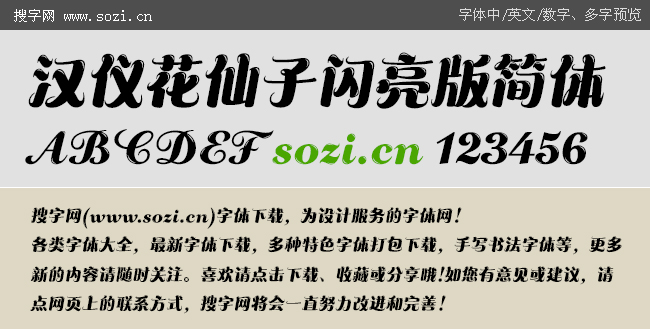
漢儀花仙子閃亮版簡體
搜字網(wǎng)給大家提供一款漢儀花仙子閃亮版簡體中文字體下載,漢儀花仙子閃亮版簡體字體從西文點(diǎn)尖書法中獲取靈感,西文書寫的優(yōu)美曲線與漢字書寫的規(guī)整造型碰撞,生長出了一款極繁主義的中文花體字。字形飽滿而圓潤,以流動(dòng)曲線構(gòu)成的筆畫似植物花卉的曼妙姿態(tài),連筆設(shè)計(jì)與裝飾游絲點(diǎn)綴其間,唯美浪漫的氛圍隨之綻放。適用于畫冊(cè)設(shè)計(jì)、海報(bào)設(shè)計(jì)、包裝設(shè)計(jì)等場合使用。(本字體為個(gè)人非商用版,如需要商用請(qǐng)聯(lián)系漢儀公司購買版權(quán))